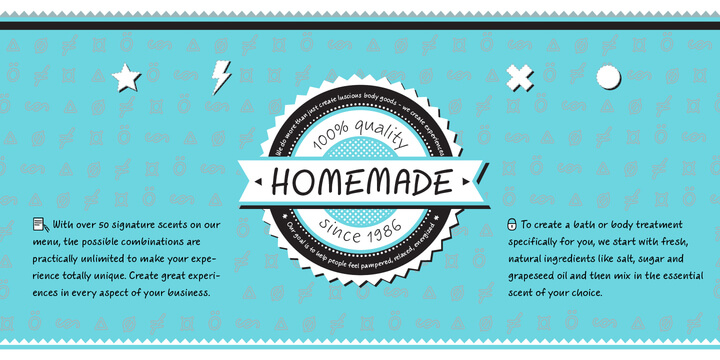
Шрифт ALS Scripticus
Это стильный рукописный шрифт, разработанный Юлией Сисмеляйнен (Julia Sysmäläinen) в студии Art. Lebedev Studio. Он имитирует естественное письмо маркером или пером, отличаясь плавными, текучими линиями и легким наклоном. Этот кириллический шрифт обладает неформальным характером: он дружелюбный, живой и немного небрежный, что придает текстам индивидуальность. Поддерживаются как латиница, так и кириллица, включая полные наборы символов для обоих алфавитов. Шрифт отлично работает в качестве акцентного элемента для заголовков или коротких текстов. Если вам нужен уникальный почерк для проекта, вы можете скачать бесплатно ALS Scripticus у нас на сайте и сразу начать творить.